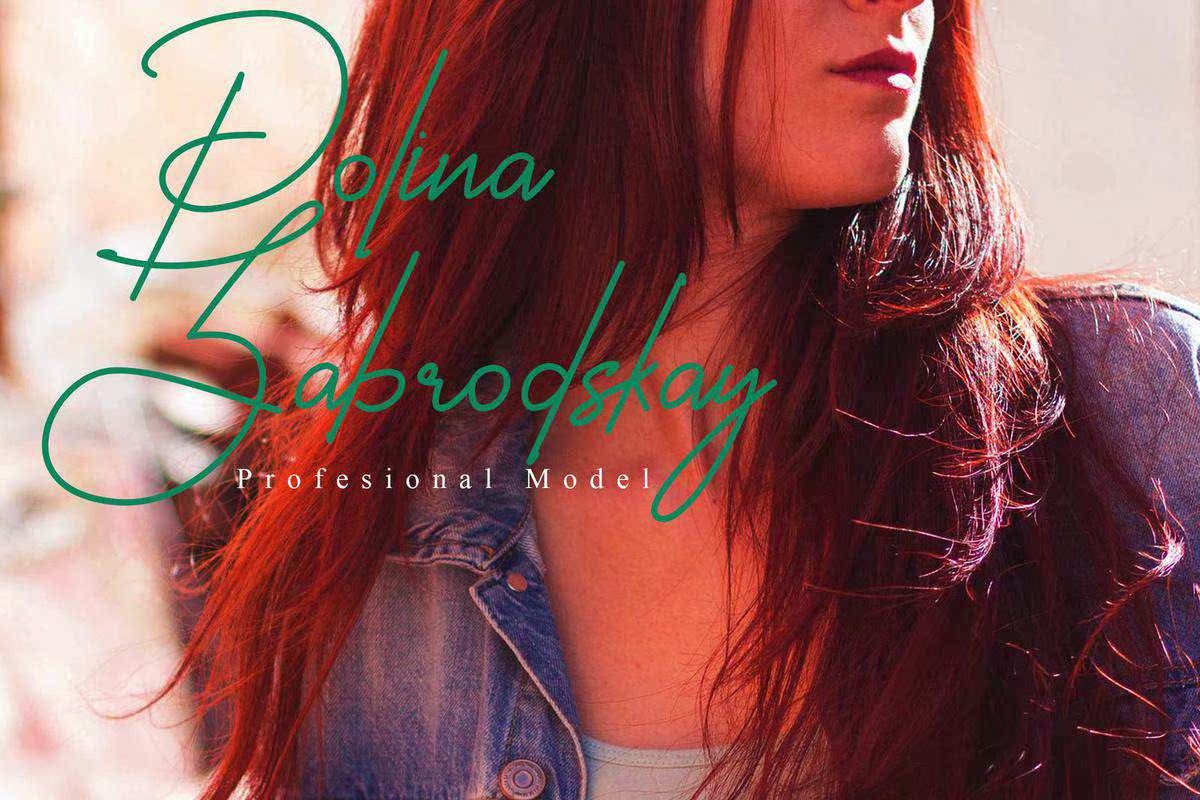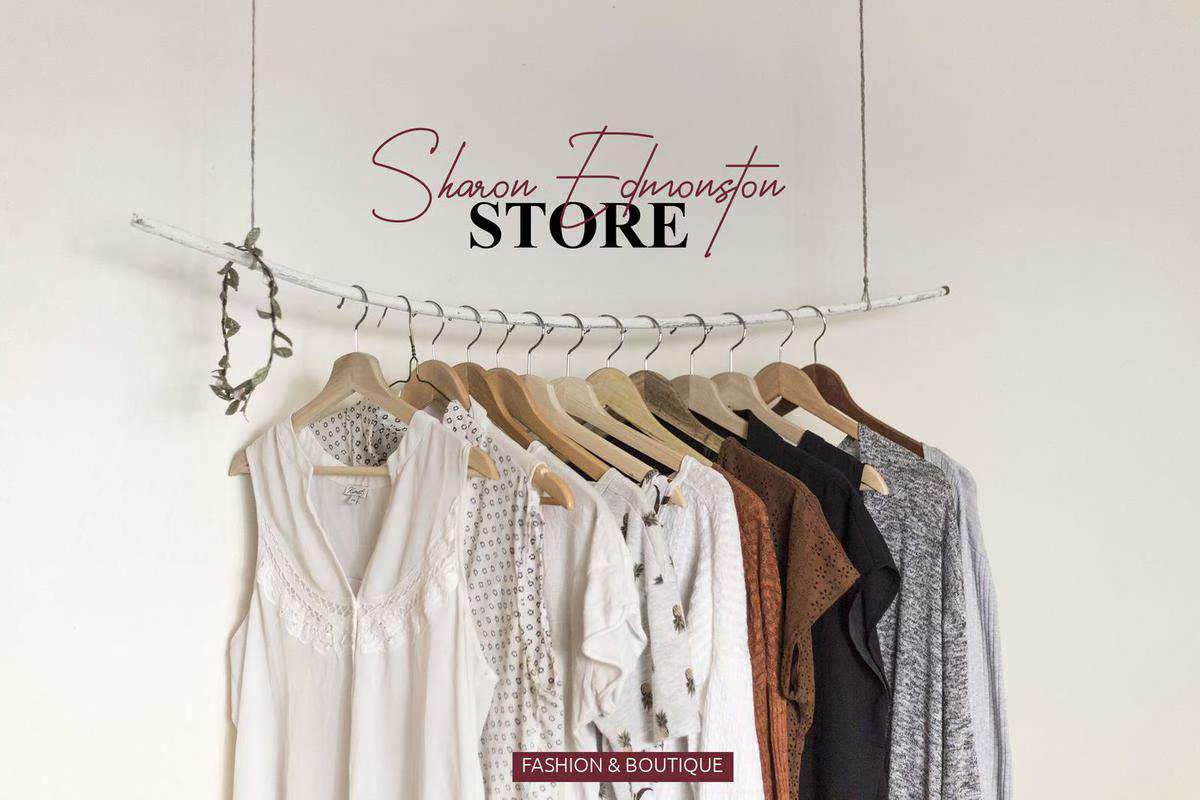
RotterdamSignatureFont—.I'tsPerfectforpersonalbranding,logo,邀请函,socialmediaposts,广告,产品包装,产品设计,标签,摄影,水印,特殊物品或任何东西。RotterdamSignatureFont—.I'tsPerfectforpersonalbranding,logo,邀请函,socialmediaposts,广告,产品包装,产品设计,标签,摄影,水印、特殊物品或任何东西。